無料で使える日本語フォント100個を紹介します。商用利用可能なものを厳選しました。
正統派フォントからオリジナルフォント、おもしろフォントまで、デザインワークに使えるフォントが揃っています。ひらがな、カタカナ、漢字、英数字がセットになっているものもあります。
1. ゴシック体(本文にも見出しにも使える)
ゴシック体のフォントを集めました。本文から見出しまで、幅広く使えます。
フロップデザインフォント シンプルなゴシック体
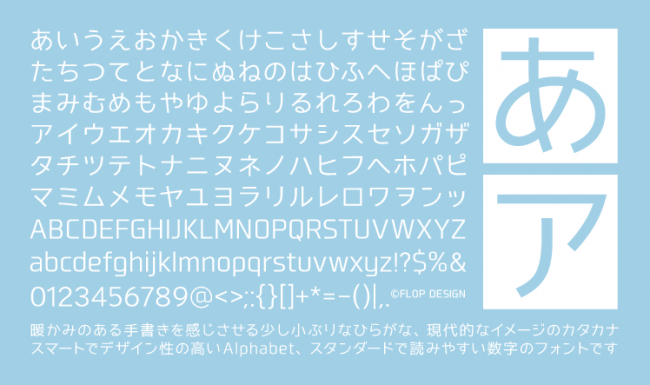
フロップデザインフォントはシンプルなゴシック体のフォントです。ひらがなは暖かみのある手書き風デザイン、カタカナはスマートなデザイン、数字はスタンダードで読みやすいデザイン、それぞれ異なるコンセプトでデザインされたフォントです。全体に統一感があり、小さなサイズでも読みやすく、WebからDTPまで幅広く使えます。
スマートフォントUI+ アプリのUIに最適なフォント
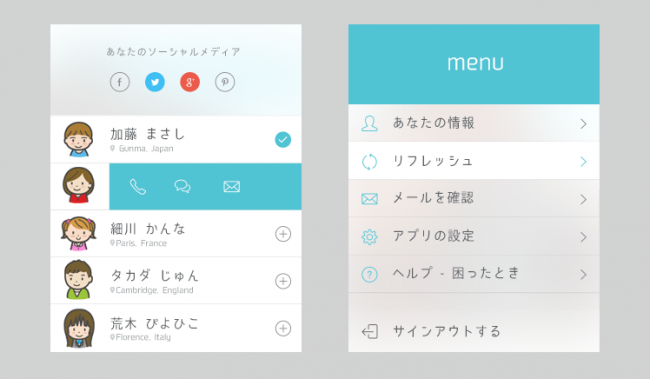
スマートフォントUI+はおしゃれでかっこいい日本語書体です。グリッド(方眼)を意識したシステマチックなデザインで、アプリなどスマートフォンデバイス上で読みやすい作りになっています。
やさしさゴシック 少し手書きの味わいがあるゴシックフォント
やさしさゴシックは少し手書きの味わいがある、使いやすいゴシックフォントです。
やさしさゴシックボールド やさしさゴシックより太め
やさしさゴシックボールドはやさしさゴシックよりも太く、見出しに使えるフォントです。
JapanSans 無料の日本語webフォント
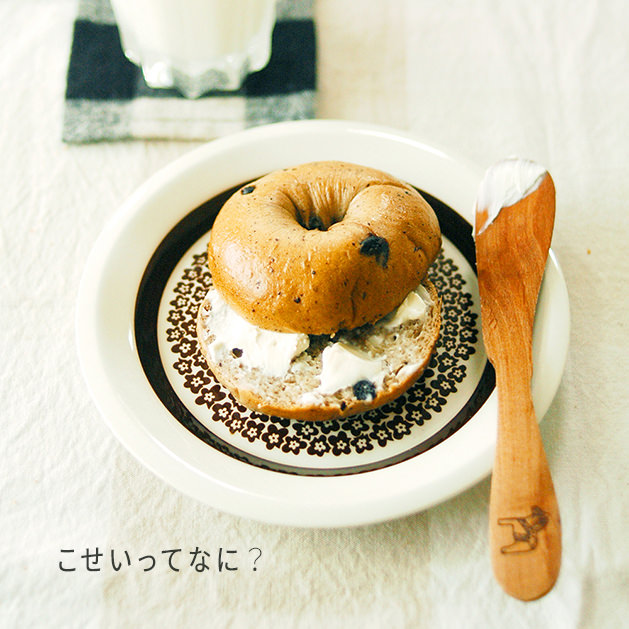
JapanSansは100%、90%、80%、70%の幅が選べる等幅では無いフォントです。狭いスペースにたくさんの文字を詰め込むような使い方もできます。
青梅ぷらすゴシックP 梅フォントとの合成フォント
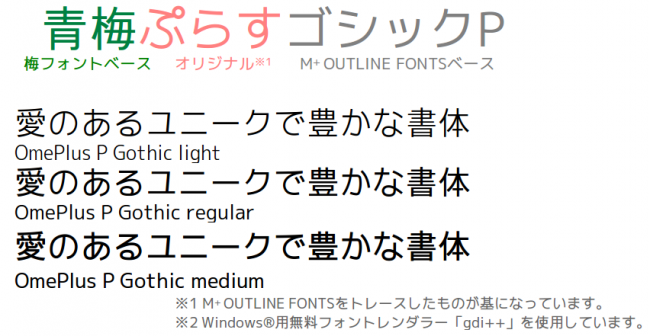
青梅ぷらすゴシックPはM+ OUTLINE FONTSと梅フォントをベースにして、オリジナルの加工を加えたフォントです。
ほのか丸ゴシック 懐かしさを感じさせる、丸ゴシック系のフォント
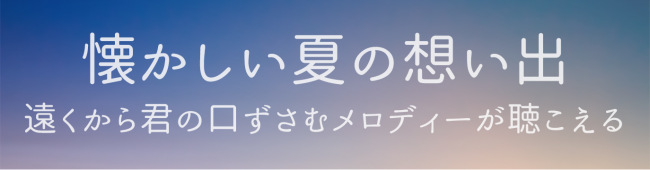
ほのか丸ゴシックは懐かしさを感じさせる、丸ゴシック系のフォントです。デザインで落ち着いた雰囲気、寂しさ、郷愁を表現したいときに使えます。
Kazesawa (かぜさわ) フォント パワーポイントに最適
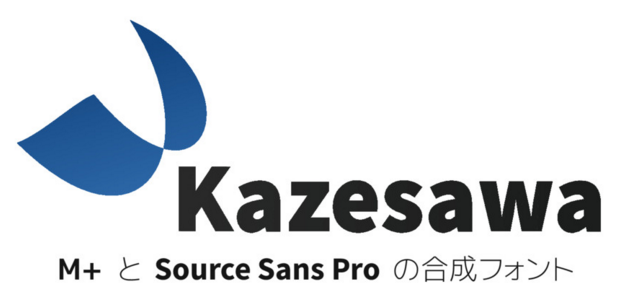
Kazesawa (かぜさわ) フォントは画面での視認性を重視したフォントです。ExtralightからExtrabold まで、6種類のウェイトが用意されています。繊細なデザインから力強いデザインまで幅広く使えます。パワーポイントなどのスライドにも最適です。
FGモダン モダンなゴシックフォント
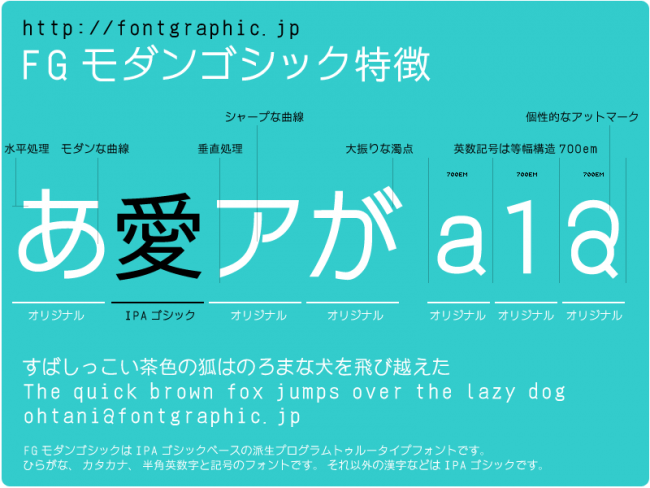
FGモダンはモダンでクールなゴシックフォントです。和欧混植の際にも、日本語の中に自然と英数字が溶けこむようなデザインになっています。ダウンロードには会員登録が必要です。
FGラブリー 個性的な曲線のフォント
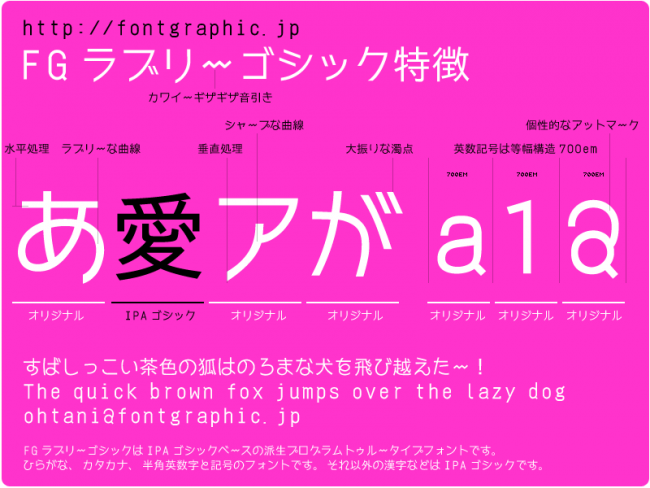
FGラブリーは個性的な曲線のフォントです。女性向けのデザインや美容室、ネイルサロンのデザインなどに適しています。ダウンロードには会員登録が必要です。
FGゼロ 零式艦上戦闘機を忠実に再現したフォント
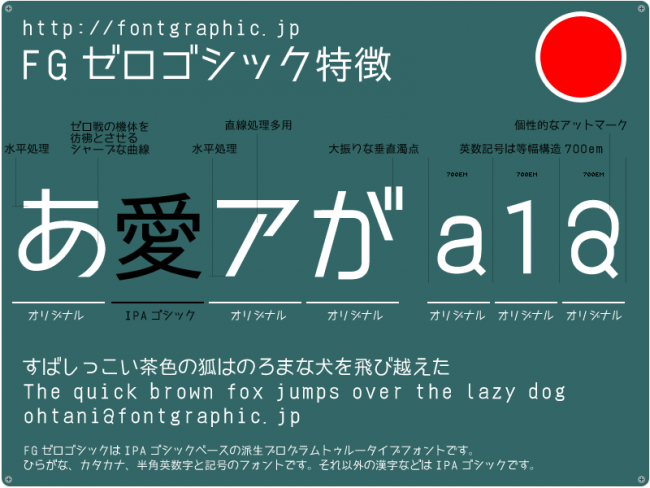
FGゼロは零式艦上戦闘機のプレートに使われていた文字を忠実に再現したフォントです。シャープでレトロな印象です。特にカタカナは一切丸みがないデザインです。ダウンロードには会員登録が必要です。
JKゴシック 女子高生風のかわいい極細フォント
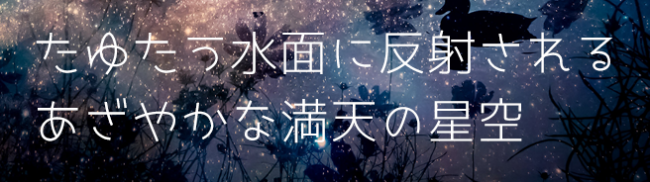
JKゴシックは女子高生風のかわいい極細フォントです。丸っこくて、こじんまりとしたかわいい文字が特徴です。
超極細ゴシック体 Extra Lightよりもさらに細い
超極細ゴシック体はExtra Light よりもさらに細い、Extra Thinの超極細日本語フォントです。超極細のボールペンで書いたようなとても細かい文字です。
源暎ゴシック 動画テロップに使える
源暎ゴシックは源ノ角ゴシックをベースに、動画でのテロップ作成を目的に作成され、文字詰めができないオフィスソフトやフリーソフトでの使用に適しています。源ノ角ゴシックに比べると文字が詰められており、英数字の文字サイズが大きめになっています。横書き用のため、縦書きでは源真ゴシックの使用がおすすめです。
源暎ラテゴ / 源暎ラテミン テロップに使える
源暎ラテゴ / 源暎ラテミンはニュースなどのテロップに使われるタイポス系のフリーフォントです。大きなサイズで使ってもスッキリとした表現ができるのが特徴です。
刻ゴシック Light フォント 直線的なひらがな、カタカナ
刻ゴシック Light フォントは従来のひらがな、カタカナに比べて直線的な形に仕上がっています。一般的なひらがな、カタカナと比べて独特な雰囲気があります。
ぼくたちのゴシック ちょっと太めで、子供っぽい日本語フォント
ぼくたちのゴシックはちょっと太めで、子供っぽい日本語フォントです。
ぼくたちのゴシック2レギュラー やわらかい印象のゴシックフォント
ぼくたちのゴシック2レギュラーはやわらかい印象のゴシックフォントです。ぼくたちのゴシックに比べて全体的に丸みがあります。親しみやすい角ゴシックです。
ぼくたちのゴシック2ボールド
ぼくたちのゴシック2ボールドはぼくたちのゴシック2レギュラーよりすこふし太めの角ゴシックです。見出しデザインにも使えます。
2. 明朝体(本文にも見出しにも使える)
明朝体のフォントを集めました。本文から見出しまで、幅広く使えます。縦書きに使えるフォントもあります。
うつくし明朝体+ モダンな明朝体
うつくし明朝体+はモダンなデザインの明朝体です。オールドスタイル明朝体は、基本的に縦書きの流れを重視して作られていますが、うつくし明朝体は、横書きでも使えるようにデザインされています。オールドスタイル明朝体の柔らかさ、レトロな味わいを残しつつ、横へのつながりを感じさせるデザインになっています。
はんなり明朝
はんなり明朝はやわらかくて、ふんわりとし明朝体です。
こころ明朝体 ほっそりとした明朝体
こころ明朝体は少しほっそりとした丸みのある明朝体フォントです。
ほのか明朝 柔らかな明朝体フォント
ほのか明朝は懐かしい日本を感じるような、柔らかな明朝体フォントです。デザインに透明感、艶やかさ、澄み切った感じを表現したいときにおすすめです。少し癖のあるやわらかなかな文字が特徴です。
花園明朝 全漢字を収録
花園明朝はあらゆる漢字を収録した明朝体フォントです。漢字81,390字と異体字8,793字が収録されています。
はれのそら明朝 角丸のすっきりとした明朝体
はれのそら明朝は角丸のすっきりとした明朝体です。オールド系明朝体の特徴を残しています。
あおぞら明朝 極細、極太の明朝体フリーフォント
あおぞら明朝は極細、極太の明朝体フリーフォントです。標準的に使えるデザインの明朝体フォントです。ウェイトも揃っており、印刷物など幅広く使えます。
刻明朝 Regular フォント 小さなひらがなとカタカナ
刻明朝 Regular フォントは漢字に比べて小さなひらがなとカタカナを組み合わせたフォントです。ひらがな、カタカナの独特のエレメントが特徴です。
3. M+ FONTS(高品質なゴシック体フォント)
日本語フォントとして有名なM+ FONTSです。有料フォントと比べても遜色ない高品質なフォントで、無料で提供されているのが信じられないレベルです。
M+ FONTS 直線処理と柔らかな曲線の対比
M+ FONTSは10年以上の年月をかけて制作が続いている、高品質なフォントです。和文セットのM+ Type-1は直線と柔らかな曲線でデザインされており、特に細いフォントが綺麗です。ミニマルなデザインに合います。かな文字と漢字5000文字以上が揃っているので、基本的な日本語の文章であればほぼ完全に表現することができます。欧文フォントも揃っています。
Mgen+ (ムゲンプラス) M+ FONTSの漢字を補ったフォント
Mgen+ (ムゲンプラス)はM+ FONTSの漢字を源ノ角ゴシックで補ったフォントです。M+ FONTSは制作開始から10年が経過し、JIS第一水準すべてと、JIS第二水準の約半数の漢字が使えるようになりました。常用では問題なく使用できますが、地名や固有名詞など難しい漢字に未収録のものがあります。それらの漢字を源ノ角ゴシックで補い、約14000文字以上(JIS第1~4水準すべてを含む)の漢字が使用できます。
自家製 Rounded M+ M+ FONTSを加工した丸ゴシック体
自家製 Rounded M+はM+ FONTSに加工を施して、丸ゴシックにしたフォントです。第一水準漢字のすべてと、第二水準漢字の一部の 4,972 字が含まれています。本家 Rounded M+と比べると、使える漢字が増えているなどバージョンアップしています。
Rounded Mgen+ 自家製 Rounded M+の漢字補完版
Rounded Mgen+は自家製 Rounded M+の漢字を源ノ角ゴシックで補うことで、より豊富な漢字、記号を使えるようにしたバージョンです。約14000文字以上(JIS第1~4水準すべてを含む)の漢字が使用できます。
Koruri M+ FONTSとOpen Sansの合成フォント
KoruriはM+ FONTSをベースに英数字グリフがOpen Sansに差し替えて調整が施されています。
4. 源ノ角ゴシック(和文フリーフォントの最上位)
AdobeとGoogleが共同開発した源ノ角ゴシック(Source Han Sans)です。和文フリーフォントの中で、最上位のクオリティで幅広く使えます。
源ノ角ゴシック 和文フリーフォントの最上位
源ノ角ゴシックはAdobeとGoogleが共同開発したオープンソースのサンセリフゴシック体フォントです。WEBフォントやAndroid OS搭載を目的に作成されました。ヒラギノや小塚ゴシックに負けない美しいフォントで、メリハリがあり、モバイルデバイスなどで縮小して表示しても文字が潰れにくいのが特徴です。ウエイトは極細から極太まで7種類用意されています。日本語だけでなく、中国語(簡体字、繁体字)、韓国語の文字がセットになっているので、多言語サイトのデザインにも利用できます。
源真ゴシック パワポで使える
源真ゴシックは源ノ角ゴシックをTrueType 形式に変換し、オフィスソフトなど普段でも使いやすいようにカスタマイズしたフォントです。PhotoshopなどのAdobeソフトでは源ノ角ゴシック、PowerPointやWordでは源真ゴシックを使うのがおすすめです。縦書用にも調整されています。
源柔ゴシック 丸ゴシック風
源柔ゴシックは源ノ角ゴシックの角を加工して、丸ゴシック風にしたフォントです。TrueType 形式に変換されているので、PowerPointなどオフィスソフトにも使えます。
5. ポップなフォント(ロゴ・見出し・バナーに使える)
ロゴや見出し、バナーに最適なフォントを集めました。ポップなものや太めのもの、特徴的でインパクトがあるものなど、ロゴや見出し、バナーデザインのフォントとして使えます。
かんじゅくゴシック ガタガタとした独特のラインが魅力的
かんじゅくゴシックはガタガタとした独特のラインが魅力的な、味わい深いフォントです。見出しやバナーに利用するだけで、デザインにインパクトを出すことができます。
ロゴたいぷゴシック ロゴのためにデザインされたフォント
ロゴたいぷゴシックはロゴタイプや見出し向けの日本語フォントです。漢字も含まれています。ロゴ向けのフォントのかっこいい感じと、少し優しいエレガントな雰囲気のデザインが特徴です。
ロゴたいぷゴシック-コンデンスド オシャレなロゴ向けフォント
ロゴたいぷゴシック-コンデンスドは少しコンデンスド(長体 = 縦長)なフォントです。優しさとエレガントさを感じさせる独特のデザインです。
にくまるフォント ゆるくて、てきとうなフォント
にくまるフォントはロゴデザインや見出しに使えるフリーフォントです。漢字も含まれています。ゆるくて、てきとうな、柔らかい雰囲気のデザインが特徴です。
FGポップ 直線的で元気なフォント
FGポップはロゴデザインにも使えるポップなフォントです。直線が特徴的な元気のいいデザインです。ダウンロードには会員登録が必要です。
※2017/04/02 フリーフォントは廃止されました。
コーポレート・ロゴ
コーポレート・ロゴは企業やサービスのロゴで使われているようなモダンでシンプルなロゴ文字です。そのままロゴタイプとして使うことができます。
ラノベPOPフォント 同人誌やアニメで使える
ラノベPOPフォントは同人誌やアニメで使える、ポップなフォントです。軽やかで楽しい雰囲気のフォントです。マジックペンで勢いよく書いたような要素があります。
けいふぉんと! ポップ体フォント
けいふぉんと!はアニメ「けいおん!」のロゴを元に作成されたフォントです。軽快でポップなデザインのフォントで、見出しでの使用に適しています。
鉄瓶ゴシック 極太のゴツゴツフォント
鉄瓶ゴシックは極太でゴツゴツとした質感の味わい深いフォントです。ロゴやバナーデザインなどに使うとインパクトが出ておすすめです。
ゾウフォント 極太のカタカナ
ゾウフォントは見出しに使える極太のカタカナだけのフォントです。
ショウワノニヲイ 昭和のレトロなひらがなフォント
ショウワノニヲイは昭和のレトロな雰囲気のひらがなフォントです。
ふわもこフォント 雲みたいなもこもこフォント
ふわもこフォントは雲みたいにふわふわしたフォントです。白抜きなので、ロゴやバナーへの使用に最適です。
ねずみフォント 昔懐かしいフォント
ねずみフォントは絵本やちょっと古い本で使われているような、昔懐かしいフォントです。
mini-わくわくフォント 手描き風のわくわくフォント
mini-わくわくフォントはちょっと手描き風のわくわくフォントです。漢字は使えません。
オリエンタル レトロなカタカナフォント
オリエンタルはレトロな雰囲気のあるカタカナフォントです。エッジが効いていて、オリジナリオティがあります。
ニクキュウ つやのある太めのフォント
ニクキュウはつやのある太めのフォントです。カタカナだけです。
6. アンチック系フォント(漫画にも使える)
漫画などで使われるアンチック体のフォントです。ゴシック体の漢字に合わせた明朝体っぽいかなが特徴です。同人誌などでの使用におすすめです。
新コミック体 癖のない、バランスの取れたフォント
新コミック体は美しくて、癖のない、バランスの取れたフォントです。全体的にくっきりと見えるので、同人誌などにじみやすい印刷物でも使えます。縦書きにも対応しています。
源暎アンチック 漫画に使える
源暎アンチックは漫画で一番よく使われるアンチック体のフォントです。アンチック体は有料フォントが多いので、無料で利用できるものは貴重です。細身のフォントで、絵に対して主張をしすぎないようにバランスが取れています。
やさしさアンチック 同人誌やコミックにおすすめ
やさしさアンチックはゴシック体の漢字に、太い明朝体の「かな」が組み合わされた、漫画向けのアンチックフォントです。漫画の吹き出しや、辞書の見出し、絵本でよく使われるフォントです。同人誌やコミックにおすすめ。
ほのかアンティーク丸 レトロな丸ゴシック系
ほのかアンティーク丸は丸ゴシック系の漢字に明朝体のかな文字を組み合わせたアンチック系のフォントです。かしこまった雰囲気を表現したいデザインに使えます。
ほのかアンティーク角 レトロな角ゴシック系
ほのかアンティーク角は各ゴシック系の漢字に明朝体のかな文字を組み合わせたアンチック系のフォントです。かっちりとした雰囲気を表現したいデザインに使えます。
7. オリジナルフォント(手書き・オリジナル・変わり種)
手描きからオリジナルフォント、ちょっと変わったフォントまで、さまざまなフォントがあります。上手く取り入れることができると、オリジナリティのあるデザインになります。
あんずもじ フェルトペンで書いたようなフォント
あんずもじはかわいらしい独特のフォントです。フェルトペンで書いたような、手描き風の味わいと可読性が両立しています。
KFひま字ふで ぷっくりとした筆文字
KFひま字ふではぷっくりとした筆文字のようなフォントです。筆で書いたようなはらいが特徴的なフォントです。
KFひま字ワク 白抜きの手描き風フォント
KFひま字ワクは手書きのようなラフなラインの白抜きフォントです。白抜きなので、バナーデザインなどにも使いやすいです。
ふい字 漢字もいろいろ入った手書きフォント
ふい字は手描き風のオリジナルフォントです。漢字もいろいろ入っているので、かなり使えます。
おひさまフォント 元気いっぱいのフォント
おひさまフォントは元気いっぱいなフォントです。超右上がりで、元気いっぱいの女の子が書いたような文字です。
やさしさゴシック手書き 手描き風のやさしいゴシック
やさしさゴシック手書きは手描き風のやさしいゴシック体フォントです。やさしさゴシックを手書きの風にアレンジしたものです。見出しやバナーで柔らかな印象を出したお時に役立ちます。
藍原筆文字楷書 手書きの毛筆フォント
藍原筆文字楷書は一文字一文字手書きで作った、毛筆フォントです。商用利用の際はメールでの事前連絡が必要です。
あじふでフォント 筆で書いた味わいあるフォント
あじふでフォントは筆で書いたような味わいのあるフォントです。
こども丸ゴシック細め 少しにじんだ手書きフォント
こども丸ゴシック細めは丸っこいフォルムが特徴のフォントです。少しにじんだ感じがいいいい味を出しています。小学1~3年生の漢字が入っています。
こども丸ゴシック 少しにじんだ手書きゴシックフォント
こども丸ゴシックは少し太めの手描き風丸ゴシックのフォントです。小学1~3年生の漢字が入っています。
ちはやフォント+
ちはやフォント+は女の子らしいかわいい文字の手書きフォントです。第一水準漢字を網羅しています。商用利用の際は、掲示板での事前連絡が必要です。
ちはやクレヨン クレヨン風のフォント
ちはやクレヨンはクレヨンで書いたようなフォントです。商用利用の際は、掲示板での事前連絡が必要です。
殴り書きクレヨン 手書きフォント
殴り書きクレヨンはクレヨンタッチの手書きフォントです。漢字は第一水準漢字まで収録されています。
ようじょふぉんと 幼い子どもの手書きフォント
ようじょふぉんとは幼い子どもが書いたような手書き風のフォントです。この写真もどう見ても手書きですが、印字されたものです。
たぬき油性マジック チラシや店頭ポップにおすすめ
たぬき油性マジックは極太油性マジックで書いた手書き文字から作成した無料日本語フォントです。年賀状やチラシ、店頭ポップなどで手書きっぽさを出したいときにおすすめです。
まるもゴシック 丸明朝体と混色するためのフォント
まるもゴシックは丸明朝体と混色するために作られたかなフォントです。丸ゴシックがベースになっています。
よもぎフォント 縦書きもできる手描き風の等幅フォント
よもぎフォントは縦書きもできる手描き風の等幅フォントです。
はなぞめフォント 第二水準の漢字にも対応
はなぞめフォントは第二水準の漢字にも対応しているフォントです。
うたミンフォント 小2版 歌うようなフォント
うたミンフォント 小2版は歌う文字というコンセプトで作られたフォントです。明朝体ベースで、跳ねるような文字が特徴です。小学2年生までと一部の漢字が利用できます。
春 お祝いフォント お祝いに使える文字だけを収録
春 お祝いフォントはお祝いに使える文字だけを収録したフォントです。封筒のデザインなどに気軽に使えます。
夏 お祭りフォント 祭りに使えるフォント
夏 お祭りフォントはお祭りで使われる文字のみを収録したフォントです。そのままで、和風なデザインに使えます。
秋 古(いにしえ)フォント 象形文字が使える
秋 古(いにしえ)フォントは象形文字を収録した珍しいフォントです。漢字の起源とされる甲骨文字と、中国雲南省のナシ族が現在も使用している遊トンパという象形文字を収録しています。
冬 年賀状フォント 年賀状に使える文字を収録
冬 年賀状フォントは年賀状に使える文字を収録したフォントです。そのまま年賀状に使うことができます。
ふぉんとうは怖い明朝体 世にも奇妙なフォント
ふぉんとうは怖い明朝体は少し崩れた印象の世にも奇妙なフォントです。ホラー映画、恐怖小説に合うフォントです。
怨霊 ゾットするホラーフォント
怨霊は見ているだけでゾットするホラーフォントです。第二水準の漢字までカバーしているので、旧漢字を使った文字でもほとんど表現できます。漢字をカバーしているホラーフォントは珍しいので、使い勝手がいいです。商用利用は、メール連絡が必要です。
機械彫刻用標準書体フォント 工業彫刻
機械彫刻用標準書体フォントは工業彫刻で利用される文字「機械彫刻用標準書体」をデジタル化したフォントです。日本工業規格(JIS)に定められた書体をベースとしているので、独特の機能美を持っています。
地方野球場フォント 電光掲示板のフォント
地方野球場フォントは80年代の神宮球場や地方球場の電光掲示板の文字を再現したフォントです。
DiaPro 時刻表風の数字や記号
DiaProは時刻表風の数字や記号を集めたフォントです。Webフォントとしても使えます。
ピグモ 00 縦書きに使うと面白いフォント
ピグモ 00は独特のデザインが特徴のフォントです。縦書きに使うと面白いデザインになります。
マキナス Scrap 「無感情な印象」のフォント
マキナス Scrapは「無感情な印象」という独自の解釈が加わった、オリジナルフォントです。
マメロン マキナス Scrapが丸くなりました
マメロンはマキナス Scrapをベースに丸型処理を施したフォントです。
FGミディアムオールド半角 漢字が旧字体に変わる
FGミディアムオールド半角は普通に入力すると漢字が旧字体に変わる面白いフォントです。
※2017/04/02 フリーフォントは廃止されました。
数式フォント 数学の図形を取り入れたフォント
数式フォントは数学の図形を随所に取り入れたフォントです。オリジナリティ溢れるデザインです。
みつバッチフォント 六角形のフォント
みつバッチフォントは六角形を文字に当て込んだ、オリジナルフォントです。
魔法陣文様フォント 呪文っぽい模様が描けるフォント
魔法陣文様フォントはなんか呪文っぽい模様が描けるフォントです。魔力のこもった魔法陣を描くことができます。日本語フォント特集だけど、英数字記号のみです。魔法だからいいよね!
魔法陣文様フォント 猫の目覚め もっと呪文っぽいフォント
魔法陣文様フォント 猫の目覚めは、前作の魔法陣文様フォントがSFっぽいということで、より呪文っぽく作成されたフォントです。魔力のこもった魔法陣を描くときに使えます。日本語フォント特集だけど、英数字記号のみです。魔法だからいいよね!
オドリコフォント 天使が踊っているような、カタカナフォント
オドリコフォントは天使が踊っているような、カタカナフォントです。可読性は低いですが、面白いフォントです。
プラネタリウム 星が輝くフォント
プラネタリウムは夜空に映えるカタカナと英字のフォントです。カタカナには星が2個、英字には星が1個輝いています。
きずだらけのぎゃーてー 間違えだらけのフォント
きずだらけのぎゃーてーは、収録漢字のほとんどが間違っている、「漢字の書き間違い」が特徴のフォントです。一画多い、へんとつくりが逆、点の位置がおかしいなど、間違えが潜んでいます。一見正しいのに、よく見ると間違っているというにくめないフォントです。
ニコモジ+ ニコニコ動画の二次創作フォント
ニコモジ+はニコニコ動画の「ニコニコ」と「NiCONiCO」のフォントを真似てつくられた二次創作フォントです。漢字も収録されています。
ニコ角 ニコモジ+の角ゴシック版
ニコ角はニコモジ+の角ゴシック版です。文字にがっちりとした安定感があります。
自由の翼フォント アニメ「進撃の巨人」の再現フォント
自由の翼フォントはアニメ「進撃の巨人」の第二期オープニングに使われているフォントを、M+ FONTSフォントをベースにデザインして再現したフォントです。斬新なデザインです。
めんまフォント アニメ「あの花」の公式フォント
めんまフォントはアニメ「あの日見た花の名前を僕達はまだ知らない。」に登場する「めんま(本間 芽衣子)」の直筆文字を公式に再現したオリジナルのフリーフォントです。商用利用も可能です。
KHドットフォント ドットで構成されたビットマップ風のフォント
KHドットフォントは電脳フォントシリーズとして商用では有料販売されていたものを、商用でも無料で利用できるようにしたフォントです。TrueType化されており、幅広い環境で利用できます。ファミコン風などレトロなデジタル風デザインに使えます。